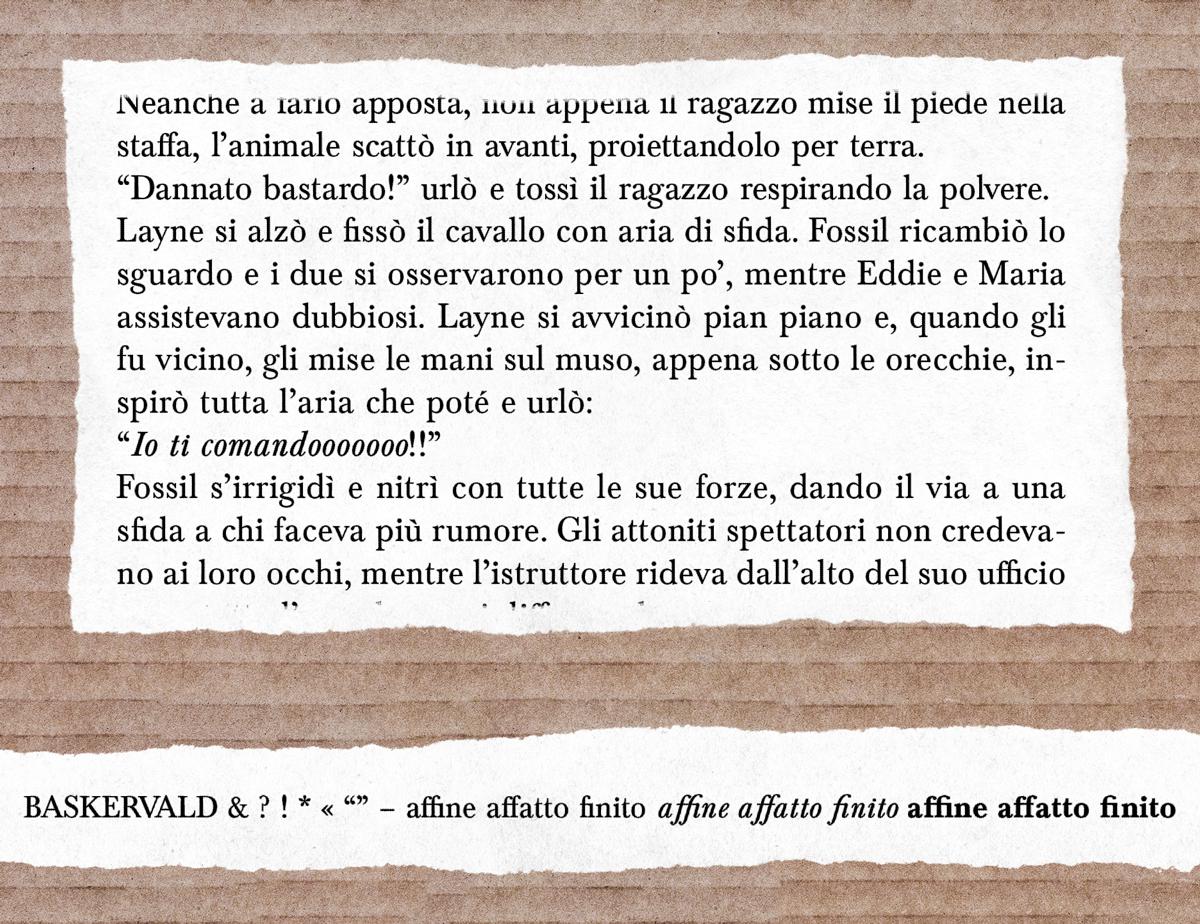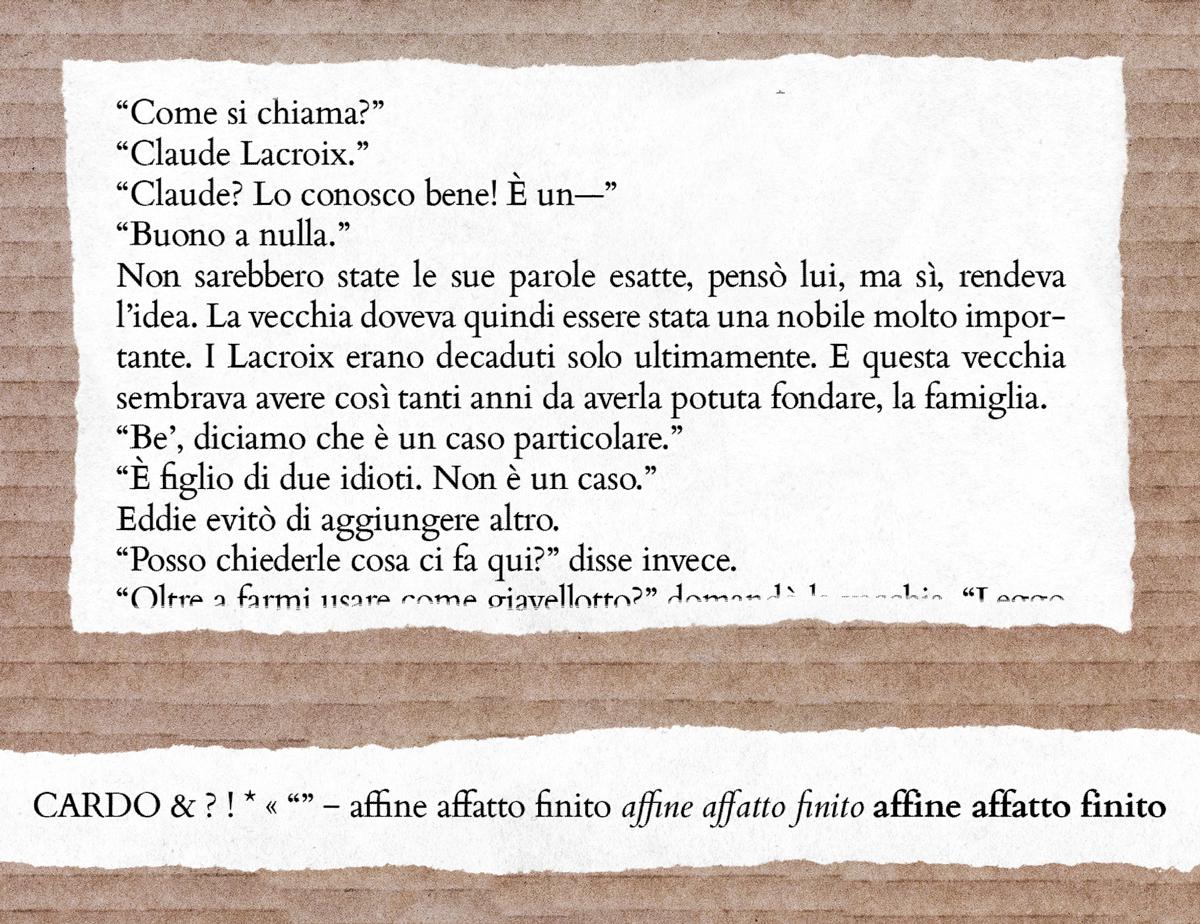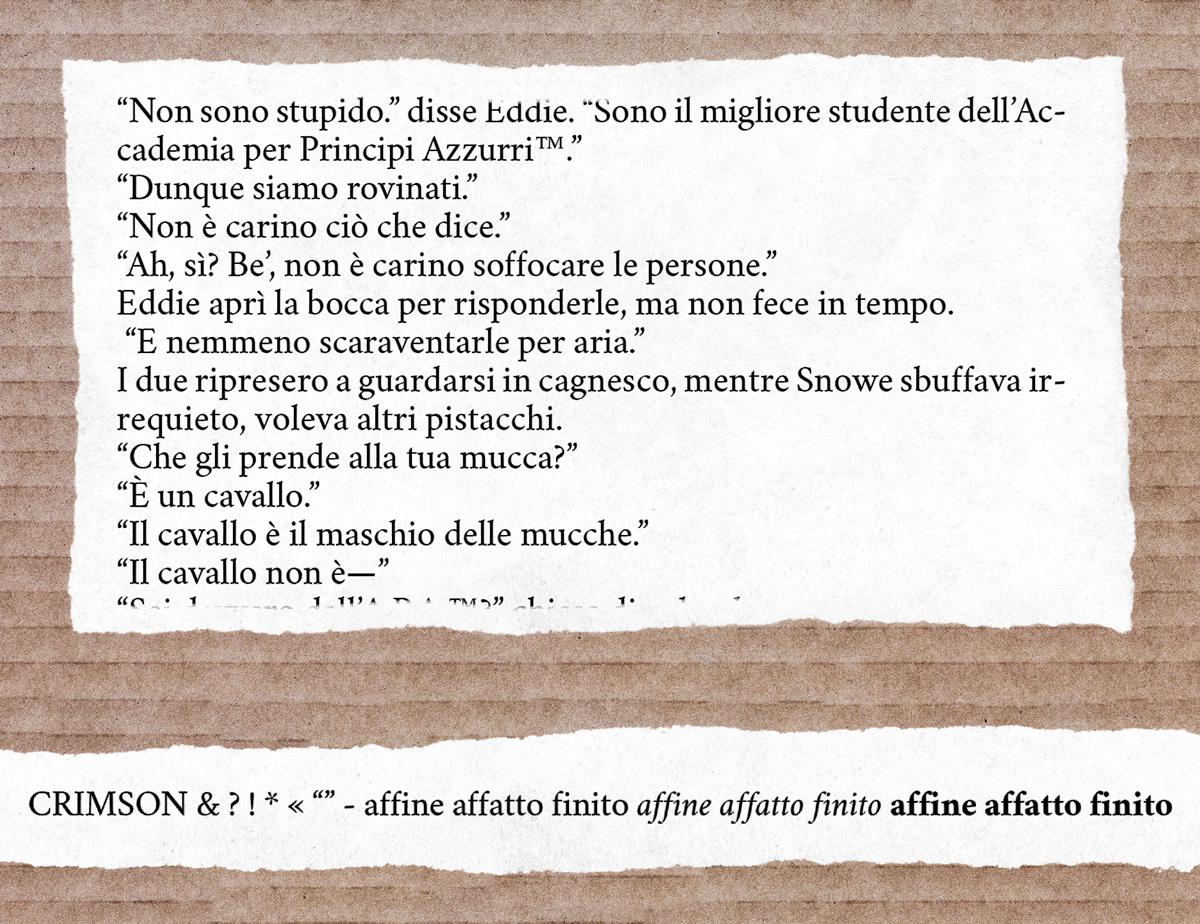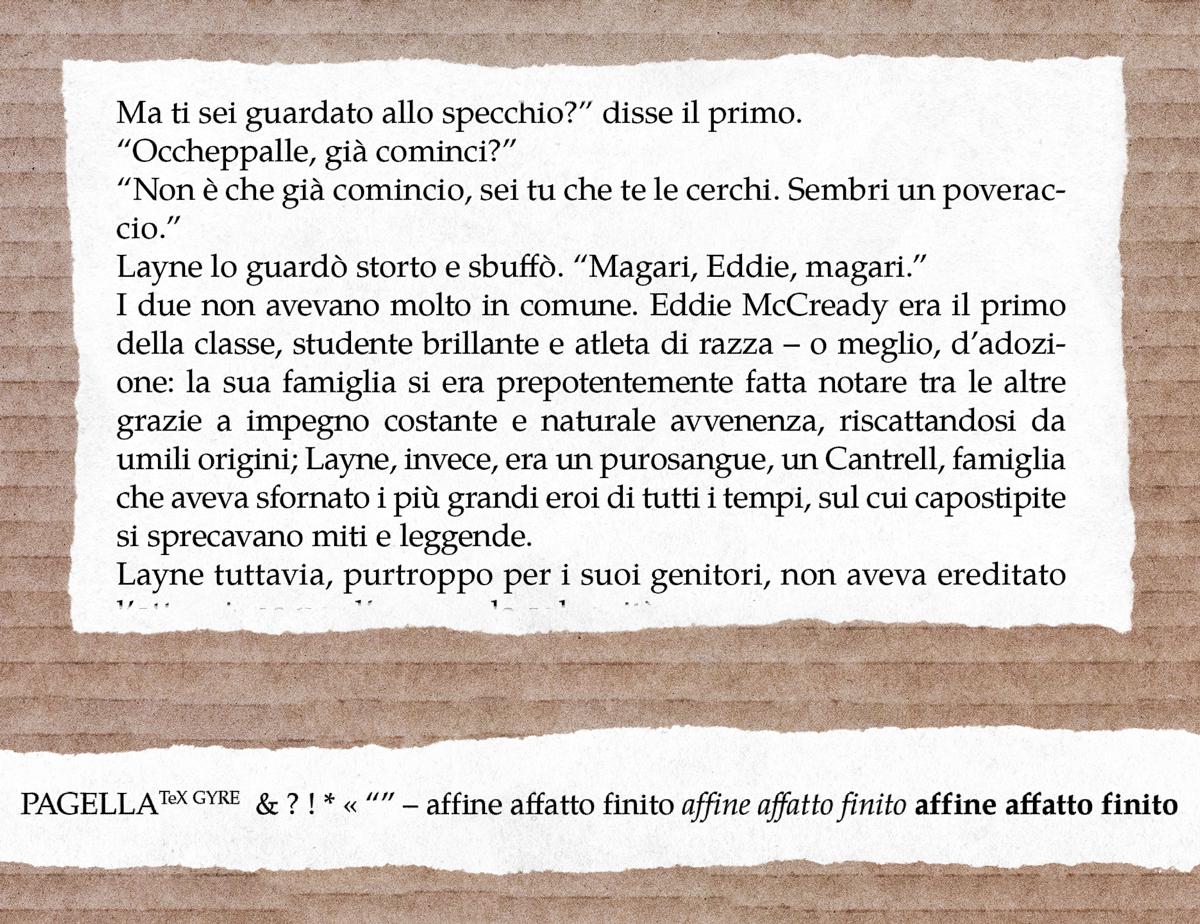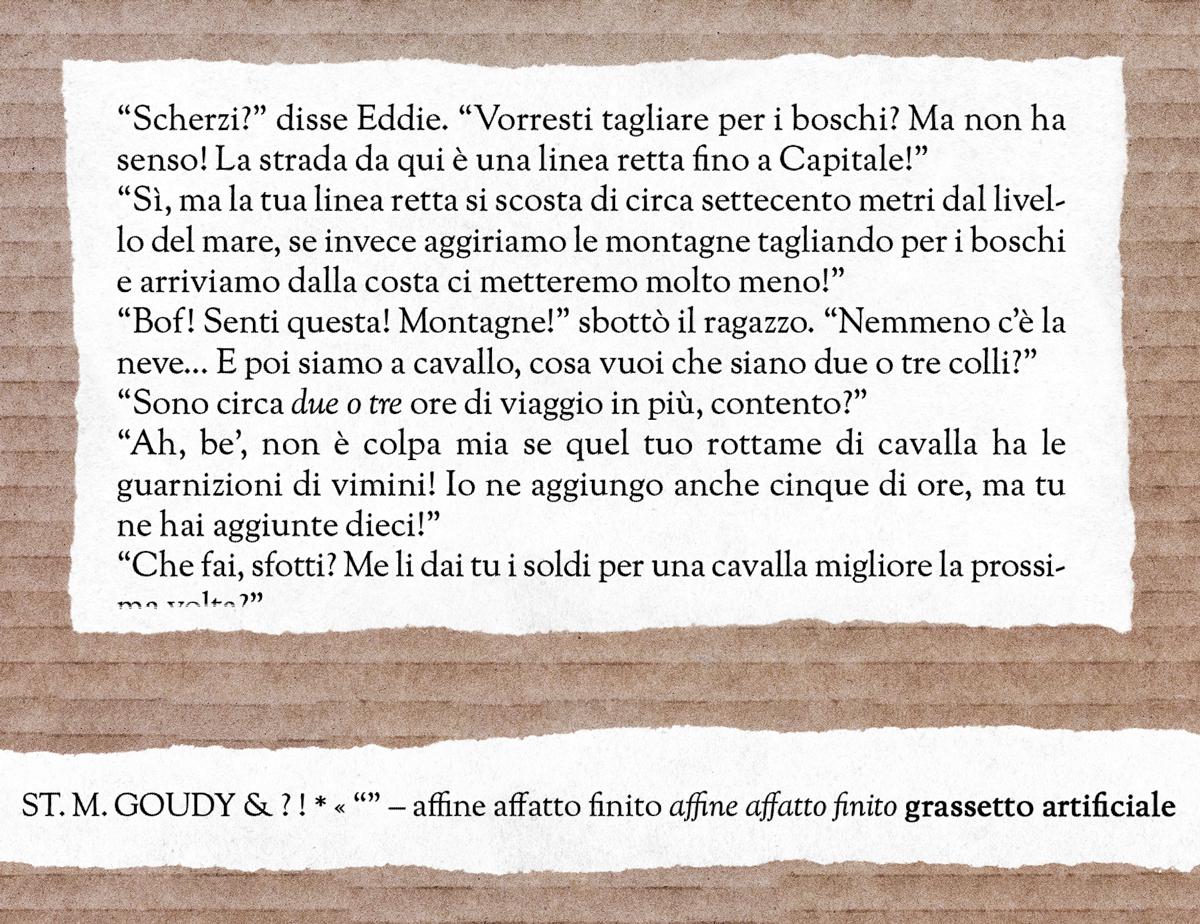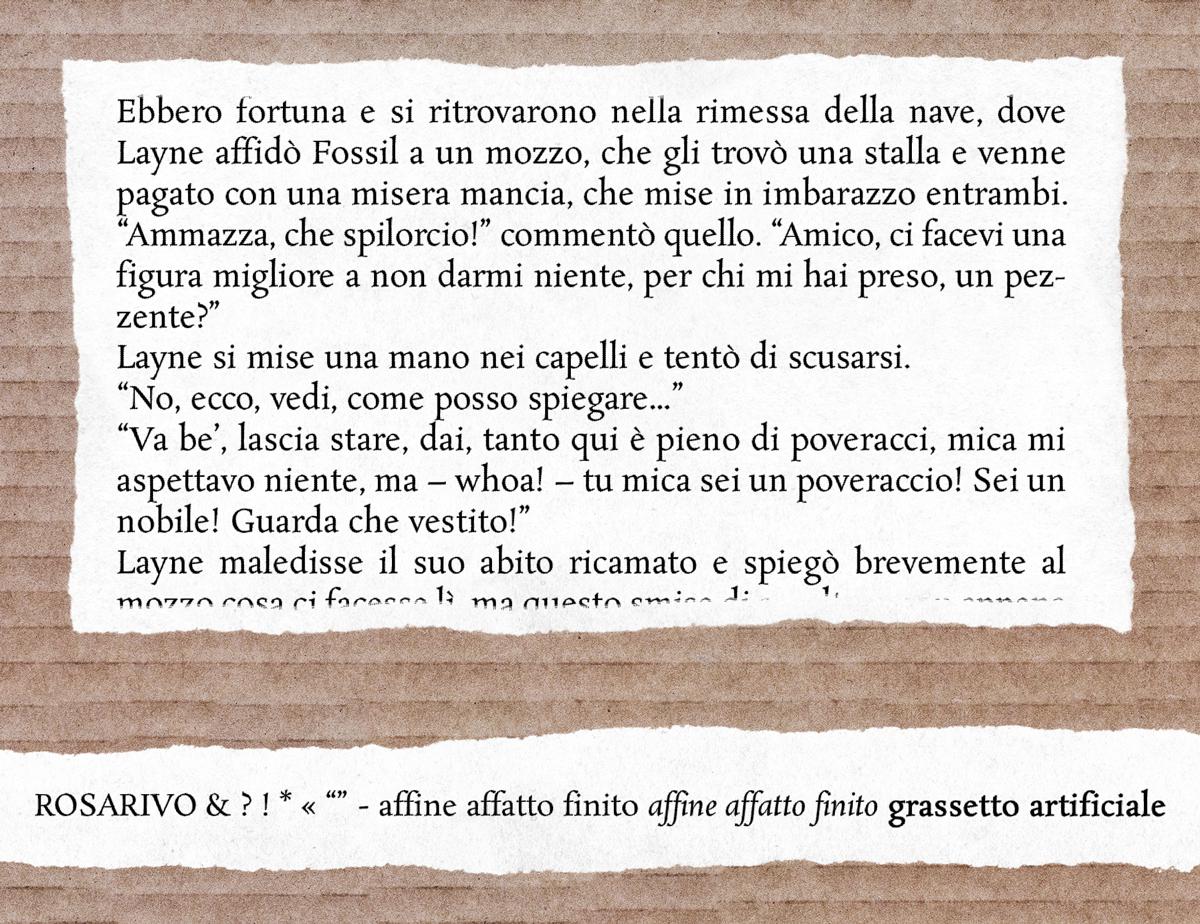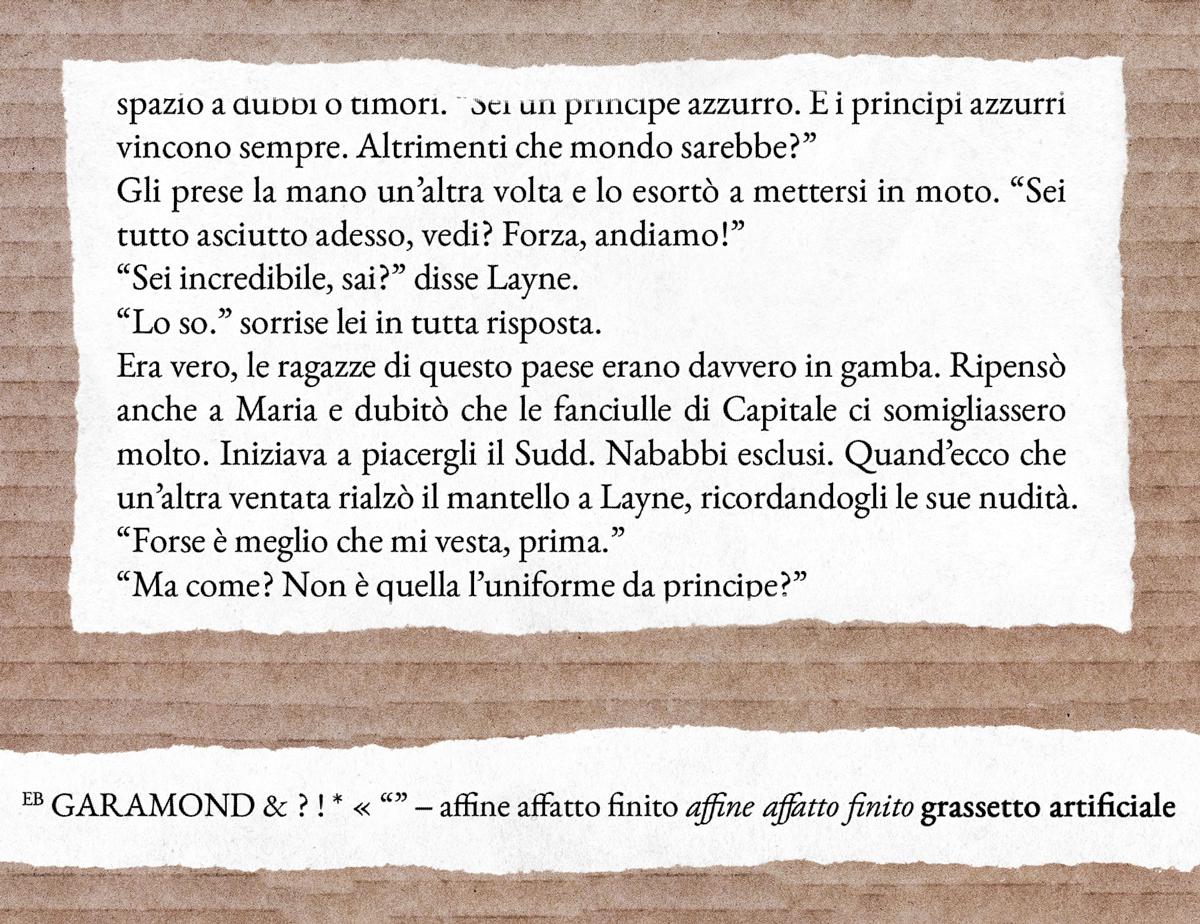
Gli aspiranti scrittori e il self publishing sono in voga da ormai qualche tempo, e sono venuti per rimanere, se mi concedi l’anglicismo. Nell’affrontare l’odissea dell’autopubblicazione, però, aldilà della qualità del testo in sé, si commettono un sacco di errori tecnici ed estetici.
Uno dei problemi più comuni è senz’altro la scelta di un font adatto alla stampa del proprio manoscritto, indipendentemente dalla piattaforma selezionata. Infatti non tutti disponiamo dei font professionali usati dalle case editrici, come l’aggraziato Simoncini Garamond o Bembo o ancora Baskerville (se siete curiosi circa quali sono i più utilizzati dalle case editrici e volete le prove, fate un salto qui).
Che font dovrei usare, allora, per impaginare un libro? Nessun problema, avranno pensato in molti, posso ricorrere a un qualsiasi font preinstallato sul mio sistema operativo, come Times New Roman, Georgia o chi per essi. Giusto?
Sbagliato.
Al prossimo libro, peggio, romanzo, stampato con Times New Roman dovranno staccarmi a badilate dal collo dell’ingenuo autore o acquirente del libro in questione. Dovranno staccarmi e sopprimermi — e assieme a me anche il malcapitato, perché sarò contagioso (spero). E non farmi nemmeno pensare a chi usa un font sans-serif, o bastone, come li si chiama a volte in Italia. Un libro stampato usando Arial o Calibri… Brr…
Quali sono le alternative per un comune mortale, allora? Che cosa posso fare se non craccare Office per ritrovarmi qualche font più decente o scaricare impunemente un font professionale?
Ma come? Non hai letto il titolo di questa rubrica? Ci sono bizzeffe, bizzeffe di font gratis e professionali là fuori. C’è solo l’imbarazzo della scelta. Ecco appunto, ce ne sono così tanti rischieresti di metterti in imbarazzo da sola/o, scegliendone uno gagliardo ma non adatto.
Lascia che ti aiuti io! Grazie al mio disturbo ossessivo compulsivo ho passato ore e ore giorni a studiare il caso e a testare decine di font diversi per il mio libro. Ogni volta che prendevo una decisione, però, il giorno dopo cambiavo idea e ricominciavo da capo. A due anni di distanza posso dire di essere guarito (e sono troppo lontano da questo passo col mio secondo romanzo per soffrire una ricaduta), quindi posso affrontare l’argomento col senno di poi.
Per la stampa di un romanzo normalmente sono indispensabili solo 2 font: il romano (leggasi dritto) e il corsivo. Il grassetto non nuoce per i titoli, anche se spesso si preferisce un font diverso ed è quindi prescindibile. In questa selezione, pertanto, ho tenuto conto esclusivamente di romano e corsivo, pur sottolineando l’esistenza o la mancanza del grassetto.
Un altro aspetto da tenere in conto è se il nostro font dispone o meno di legature, dei glifi speciali che fondono tra loro più lettere. Le legature più usate sono fi, ff e ffi. Le leggiamo continuamente nei libri senza nemmeno rendercene conto, quindi mi è sembrato giusto evidenziare se possiamo contare su di loro. Ci tengo anche a precisare che non sempre la mancanza di legature è un problema. Palatino, per esempio (il font di riferimento di Mondadori), non le usa né in romano né in corsivo, quindi, se un font ti piace, non farti problemi.
Senza ulteriori indugi, quindi (perché come avrai notato indugio con la stessa frequenza con cui respiro), ti presento i migliori caratteri gratuiti per scrivere, stampare e pubblicare libri! E anche questa volta ho le prove!
Alegreya
Alegreya è una bestia versatile e dannatamente elegante, disegnato da Juan Pablo del Peral della Huerta Tipográfica. Fa parte di una super famiglia tipografica che comprende 3 stili con corsivi e maiuscoletti (12 font in tutto) per quanto riguarda la versione serif e ben 7 stili con corsivi e maiuscoletti (28 font in tutto) nella versione sans-serif.
Come dicevo, per la stampa di un romanzo è normalmente indispensabile solo la presenza del corsivo e magari del grassetto, ma Alegreya si rimbocca le maniche e si presta ad accontentare ogni tua esigenza.
È il font con cui, dopo lungo tergiversare, ho stampato la seconda riveduta-e-corretta edizione di Non tutti i principi nascono azzurri. Inutile dire che lo trovo magnifico, insolito e anche abbastanza invisibile, perché un buon font non deve attrarre l’attenzione, ma restare sullo sfondo e lasciare spazio alla storia. Sono sicuro che Alegreya possa stupire, all’inizio, come una guida un po’ stravagante, ma come ogni buona guida prenderà per mano il lettore e si farà da parte, dopo le presentazioni.
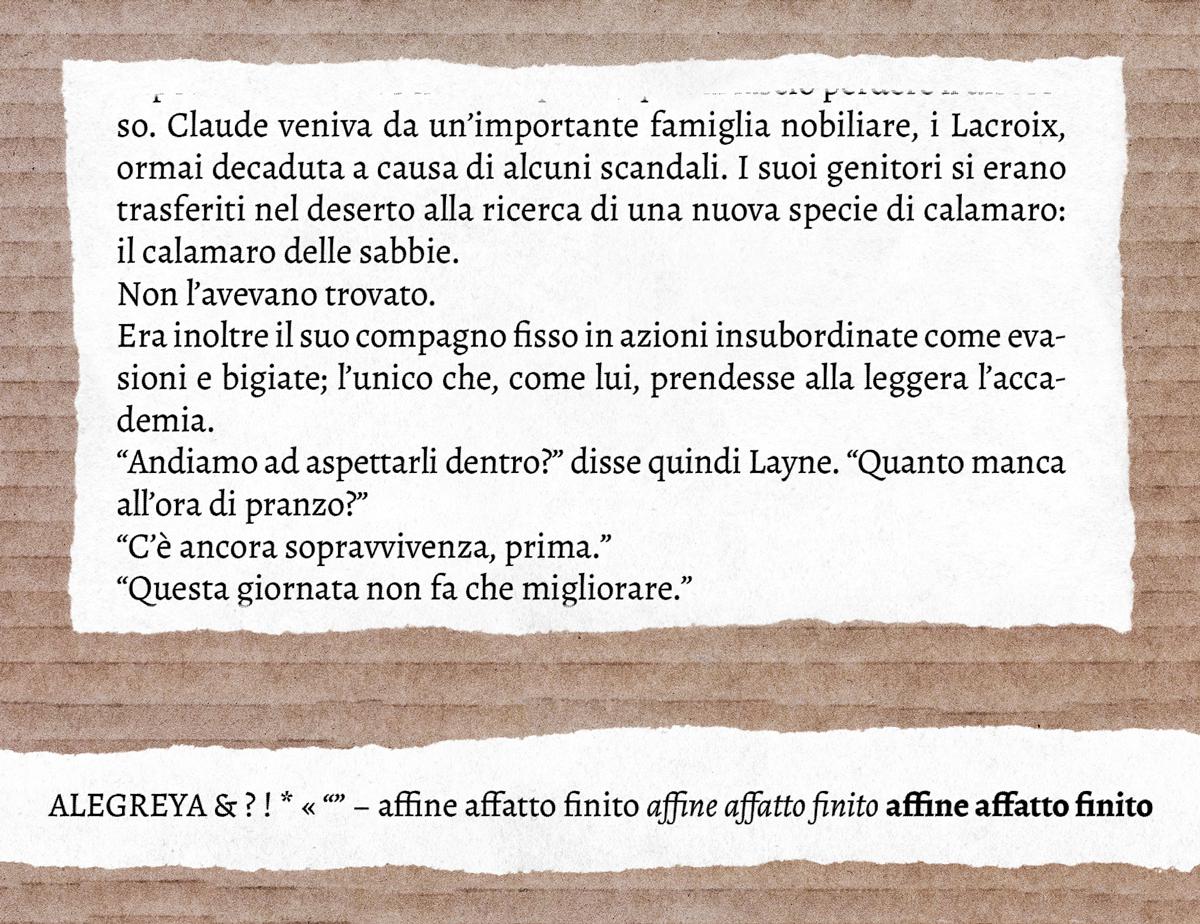
Baskervald
Baskervald è un’alternativa gratuita al font più persuasivo della storia, Baskerville. Disegnato dalla Arkandis Digital Foundry proprio per colmare questa lacuna.
Baskerville non è tra i font più utilizzati nell’editoria, non moderna, almeno, con alcune eccezioni di rilievo come Adelphi e Harper. Storicamente, invece, è stato mooolto utilizzato, cosa che ho potuto comprovare sfogliando titoli di metà novecento di mia nonna: tre su cinque usavano Baskerville, quindi non sottovaluterei questa versione gratuita di un font tanto apprezzato, poiché non è affatto inferiore all’originale.